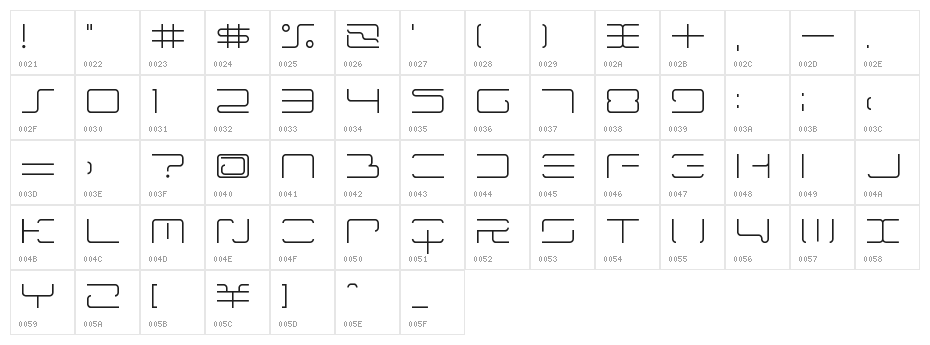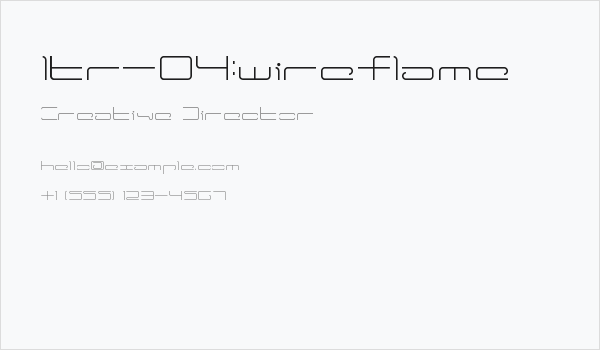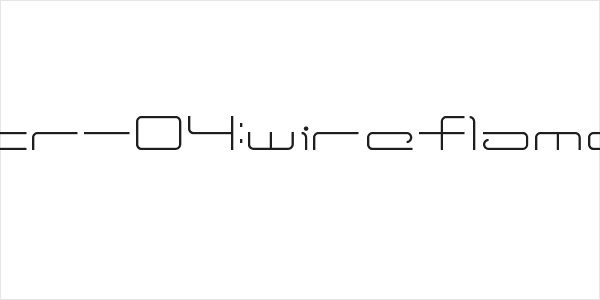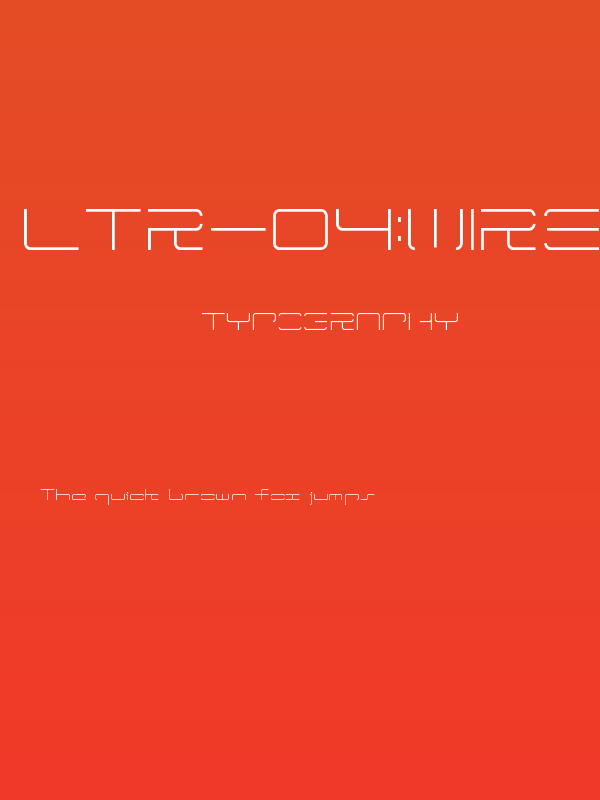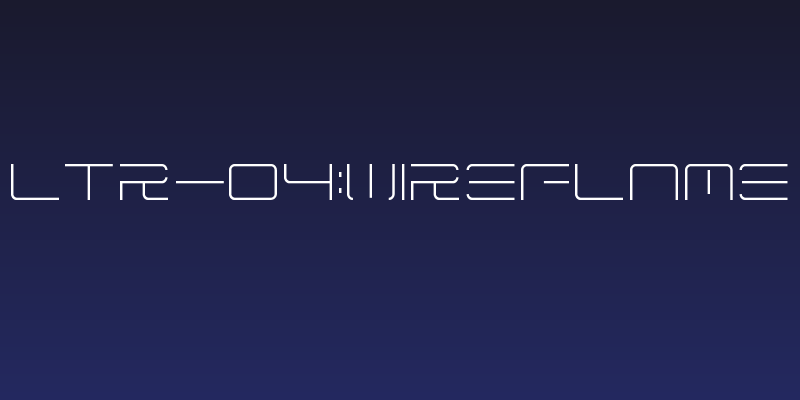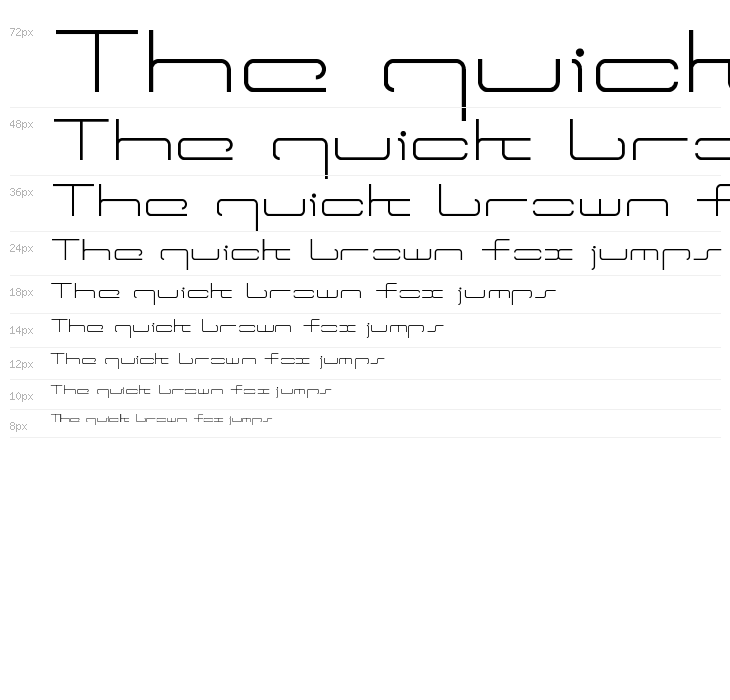
ltr-04:wireflame Font
| Caso d'uso | Logos, Headlines, Digital Interfaces |
| Progetti proposti | Ideal for tech branding, digital interfaces, sci-fi themed designs, and modern art installations. |